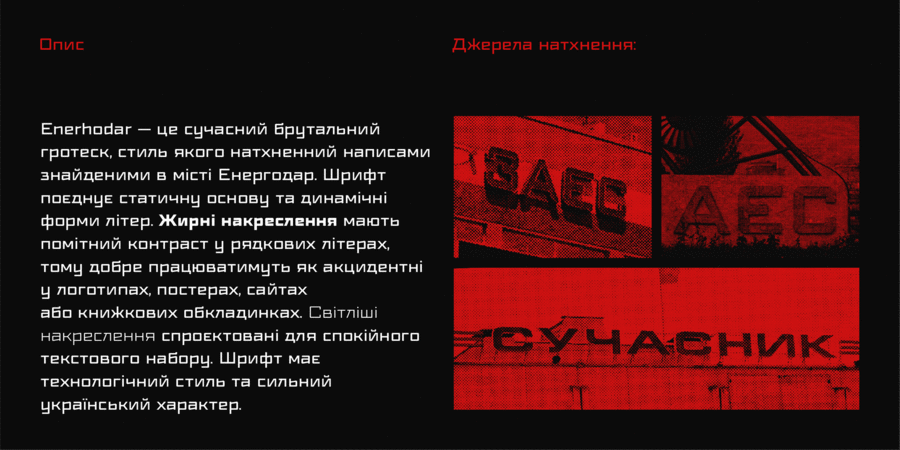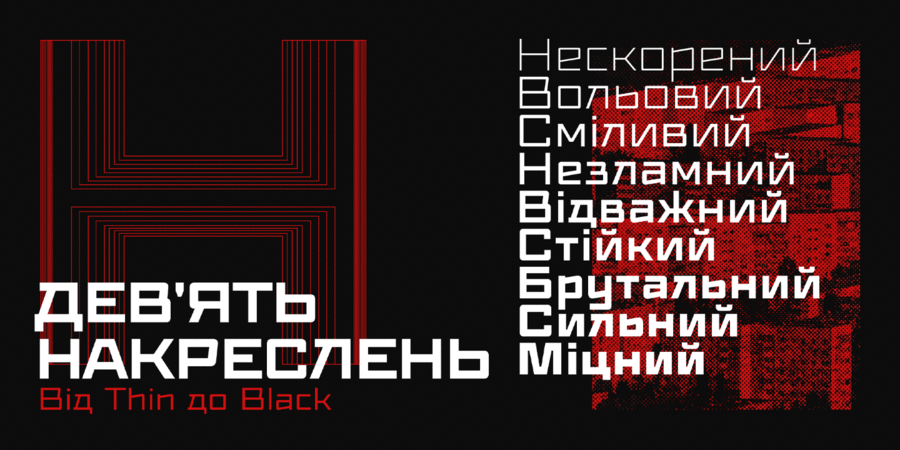
Enerhodar – це сучасний брутальний гротеск, стиль якого натхненний написами знайденими в місті Енергодар. Шрифт поєднує статичну основу та динамічні форми літер. Жирні накреслення мають помітний контраст у рядкових літерах, тому добре працюватимуть як акцидентні у логотипах, постерах, сайтах або книжкових обкладинках. Світліші накреслення спроєктовані для спокійного текстового набору. Шрифт має технологічний стиль та сильний український характер. Шрифт розробили Максим Буров і Сергій Макаренко у 2024 році.
Асоціації з сімейством шрифтів EnerhodarОсобистість і характер гарнітури:
рівний, квадратний, точний, логічний, автоматичний, техногенний, твердий, різкий, чіткий, стійкий, тонкий, легкий, прямокутний, міський, машинний, гострий, інженерний, урбаністичний, креслярський, скляний, дротяний, впевнений, сталевий, рубаний, стабільний, надійний, серйозний, переконливий, залізний, мужній, ностальгічний, гучний, сильний, кондовий, політичний, революційний, сміливий, пролетарський, індустріальний, військовий, армійський, солдатський, грубий, робочий, мотивуючий, залізничний, амбітний, незграбний, жорсткий, ламаний, елементарний, брутальний, ігровий, міцний, промисловий, значний, солідний, самостійний, відповідальний, технічний, авторитетний, суворий, якісний, обов'язковий, добротний, крутий, кінематографічний, важкий, важливий, червоний, монументальний, блатний, нахабний, спортивний, яскравий, помітний, потужний
конструктор, креслення, архітектура, інженер, автоматика, урбаністика, наука, дизайн, Місто, електроніка, технології, інструмент, робот, гра, прилад, залізо, війна, армія, зброя, машинобудування, прапор, мітинг, політика, шахта, завод, металургія, верстат, будівництво, будматеріали, тара, склад, порт, ящик, патрони, техніка, промисловість, електростанція, енергетика, ремонт, депо, шахтар, шолом, уніформа, вагон, авіація, літак, страйкбол, взуття, залізниця, робочий, страйк, Протест, кубики, лего, авто, автомат, шутер, екшен, комп'ютерна гра, паровоз, вантажівка, кіно, сейф, екскаватор, танк, тренажери, охорона, захист, блокбастер, бойовик, цегла, Барбершоп, селфі, революція, далекобійник, мотор, двигун, концерт, спорт, паливо, поліція, кіберспорт, сталевар Гарнітура має ознаки стилів: